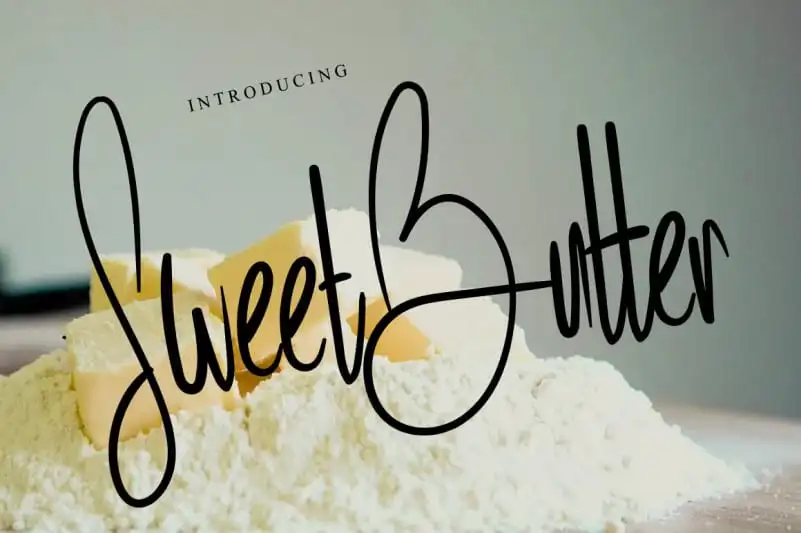
Sweet Butter Script Font – Download Grátis
A Sweet Butter Script Font é uma tipografia escrita à mão com traços finos e cífera. Esta elegante fonte dará um toque adorado a uma variedade de ideias de design. Ela adicionará um toque feliz e romântico em cada projeto, tornando-a perfeita para aqueles desejosos de dar um ar delicado às suas criações. Ideal tanto para designers gráficos quanto para quem simplesmente aprecia o brilho encantador de uma fonte escrita à mão, a Sweet Butter Script é uma escolha perfeita para criar experiências visuais memoráveis.